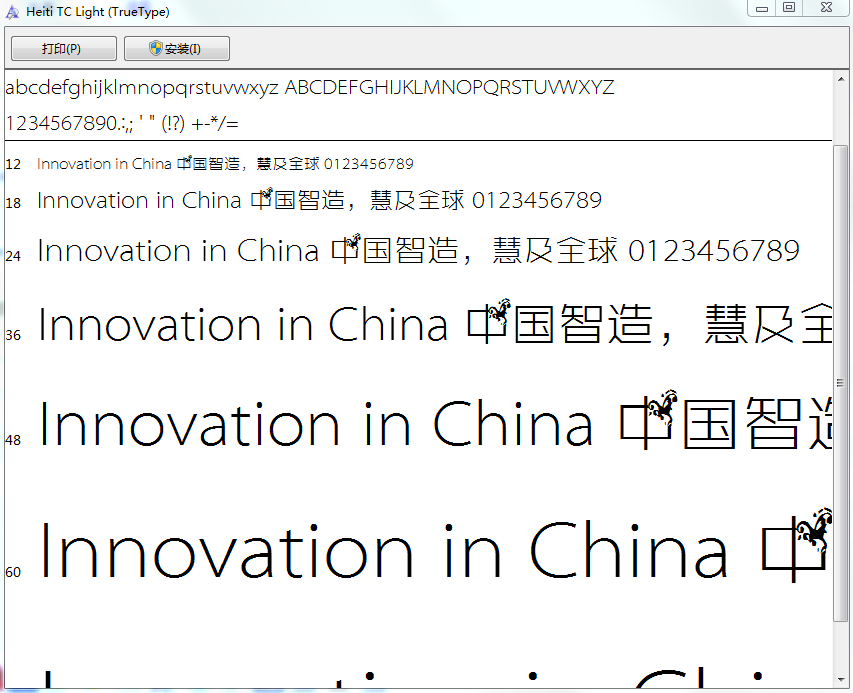
古韻美人字體是一款非常簡單清晰的字體,字體總體風(fēng)格上比較的正楷,字體上面還附帶有一個黑色的宛如古典美人的一個可愛小人,具有濃濃的古韻風(fēng)味,喜愛的朋友趕快下載體驗吧!
古韻美人字體是一款設(shè)計非常簡單的字體,它能夠為用戶提供中英文雙語字體,個別中文字加入了一些復(fù)古的元素,看起來簡單又個性。